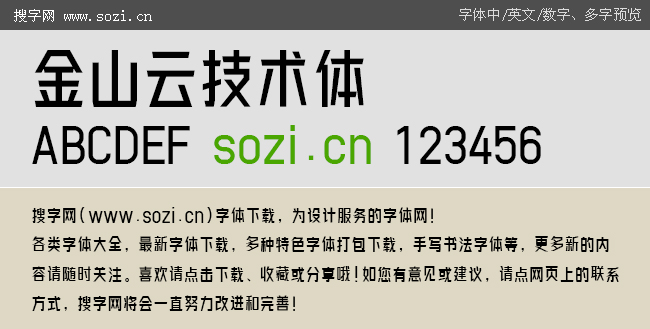
金山云技術(shù)體
搜字網(wǎng)給大家提供一款金山云技術(shù)體中文字體下載,金山云技術(shù)體是一款無襯線體,整體造型設(shè)計風(fēng)格偏向年輕、硬朗、具有活力,重新定義了字寬比例,筆畫設(shè)計根據(jù)整字權(quán)重劃分粗細進行搭配,在筆畫的銜接和末端處使用了12度的傾斜設(shè)計。字庫總字符數(shù) 7558 個。允許任何個人和企業(yè)免費使用,包括商用用途,但禁止用于違法用途。